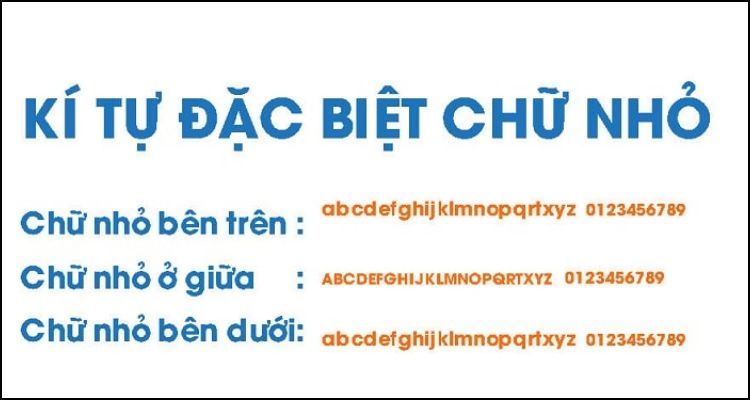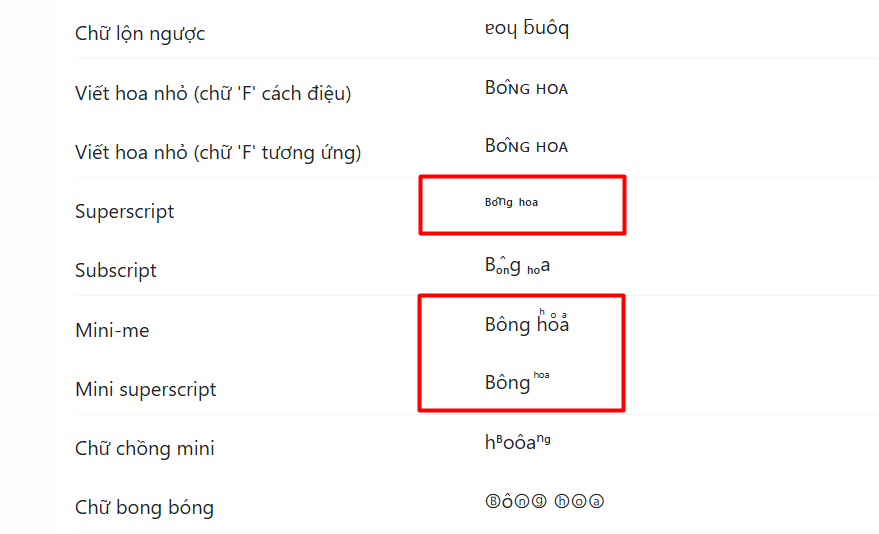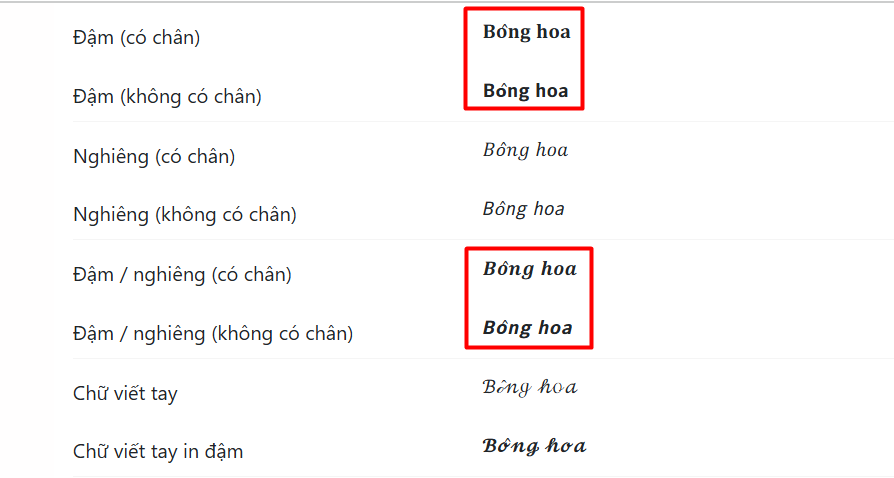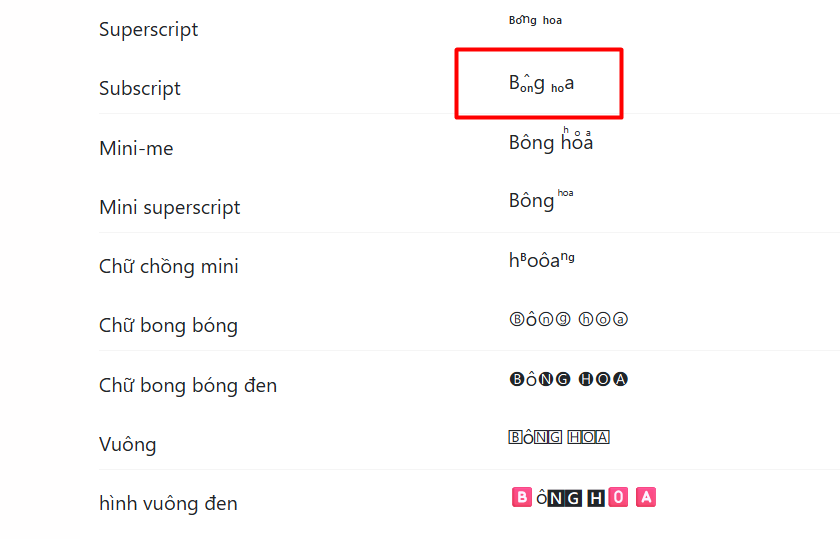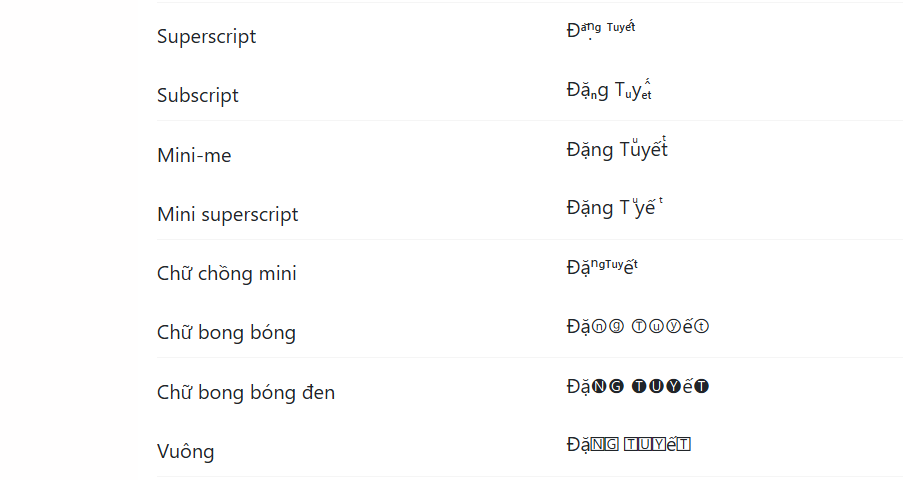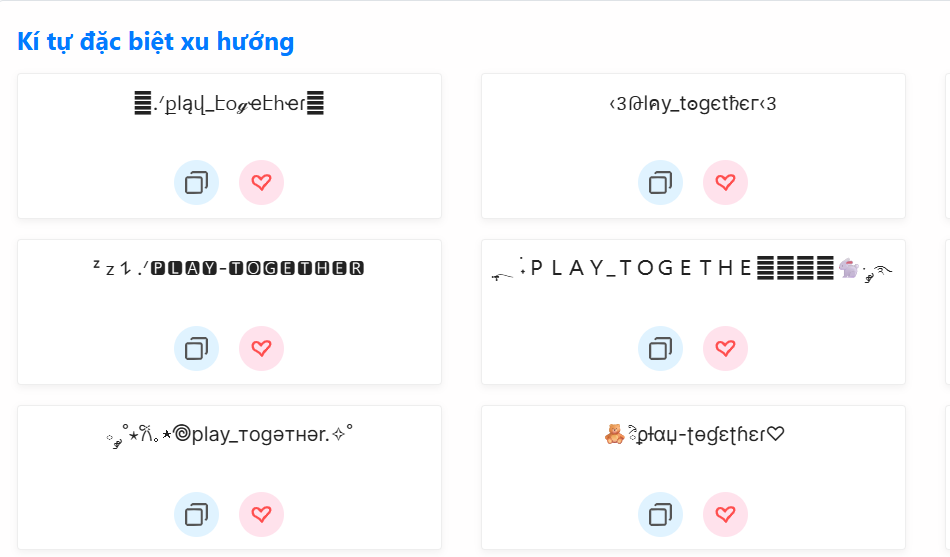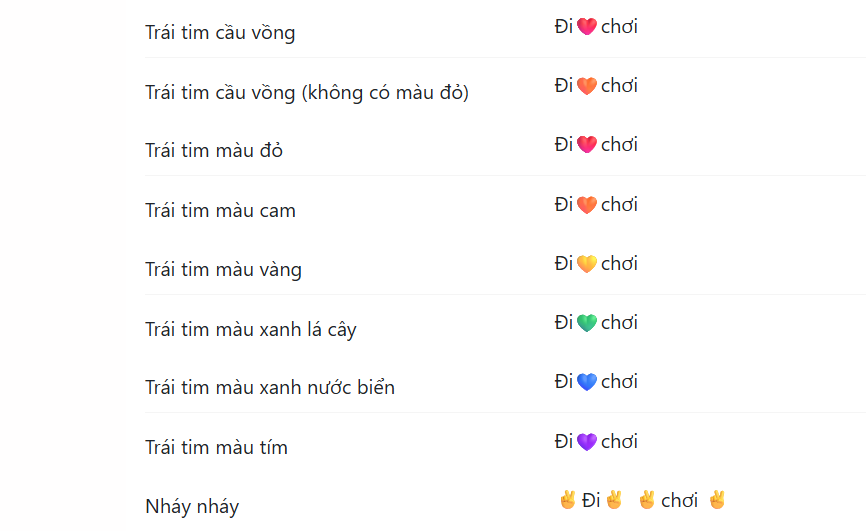
Kí tự đặc biệt chữ nhỏ không chỉ làm tăng tính sáng tạo mà còn giúp thể hiện cá tính, phong cách riêng biệt trong thế giới mạng xã hội và game. Xem chi tiết tại đây!
Ký tự đặc biệt chữ nhỏ là những biểu tượng và chữ cái có kích thước nhỏ hơn so với font chữ thông thường, được mã hóa theo chuẩn Unicode để tạo ra hiệu ứng thị giác đặc biệt. Những kí tự chữ nhỏ này đóng vai trò quan trọng trong việc tạo ra các tên kí tự đặc biệt chữ nhỏ độc đáo cho game, mạng xã hội và các ứng dụng số khác. Chúng không chỉ giúp người dùng thể hiện cá tính riêng mà còn tạo sự khác biệt và thu hút trong thế giới ảo.
Bài viết sẽ chia sẻ các nhóm ký tự chữ nhỏ phổ biến như kí tự đặc biệt chữ in hoa nhỏ, kí tự chữ nhỏ trên đầu, kí tự chữ nhỏ in đậm. Đồng thời sẽ giúp bạn nắm rõ cách sử dụng cho Facebook, Free Fire, Liên Quân Mobile, Play Together.
Những kí tự đặc biệt chữ in hoa nhỏ là những ký tự có hình dáng của chữ cái viết hoa nhưng được thiết kế với kích thước nhỏ gọn, khác biệt hoàn toàn với việc đơn thuần thu nhỏ các chữ hoa thông thường. Những kí tự đặc biệt chữ in hoa nhỏ này sẽ mang đến vẻ thanh lịch và chuyên nghiệp cho tên người dùng của bạn.
Loại ký tự này đặc biệt phù hợp với những ai muốn thể hiện sự sang trọng và đẳng cấp trong tên game hoặc profile mạng xã hội. Với kích thước nhỏ gọn nhưng vẫn giữ được độ nổi bật, chúng tạo ra hiệu ứng thị giác vô cùng ấn tượng và dễ dàng thu hút sự chú ý của người khác.
Kí tự chữ nhỏ trên đầu hay còn được gọi là ký tự superscript, là những ký tự được đặt ở vị trí cao hơn so với đường kẻ dưới của dòng chữ thông thường. Những ký tự này thuộc nhóm "Superscript" trong hệ thống Unicode, ban đầu được phát triển để phục vụ các mục đích khoa học như ghi chú công thức toán học và ký hiệu hóa học.
Kí tự chữ nhỏ trên đầu tạo ra hiệu ứng thú vị khi được đặt ở vị trí cao hơn so với dòng chữ chính, giúp tên của bạn nổi bật mà vẫn giữ được tính tinh tế. Đây là lựa chọn hoàn hảo cho những ai muốn tạo ra sự khác biệt mà không quá phô trương. Những ký tự này thường được sử dụng để thêm các từ ngắn, biệt danh, level game hoặc những thông tin phụ vào sau tên chính.
Kí tự đặc biệt chữ nhỏ mở ra một thế giới sáng tạo vô hạn cho việc cá nhân hóa tên game và profile mạng xã hội của bạn. Qua việc tìm hiểu các loại kí tự đặc biệt chữ cái nhỏ trên đầu, in đậm, ở dưới và số, bạn đã nắm được công cụ mạnh mẽ để tạo ra sự khác biệt trong thế giới số. Hãy sử dụng bộ sưu tập 1932 kí tự đa dạng này để biến tên của bạn thành một tác phẩm nghệ thuật độc nhất vô nhị.